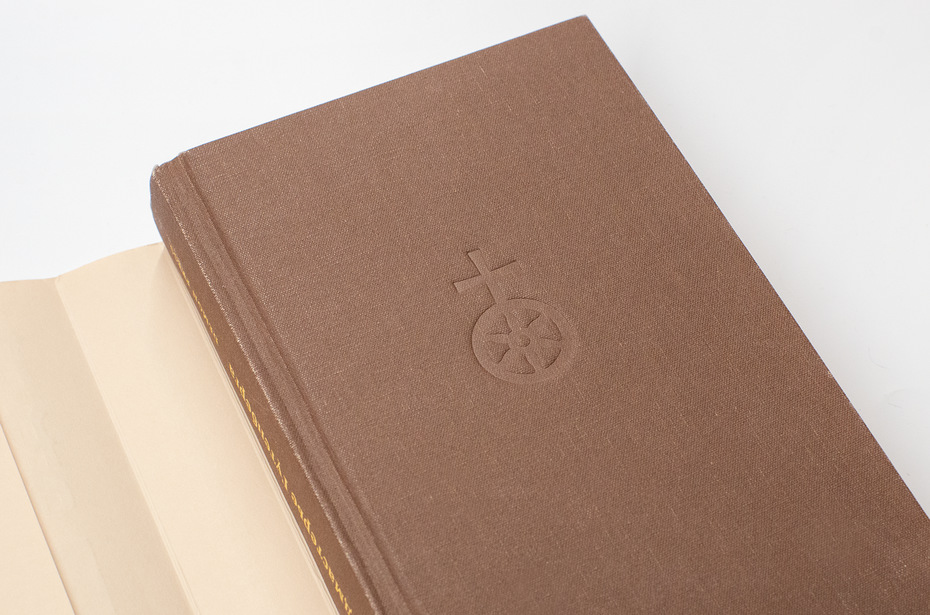
Интервью с «Демонами печати»
На рус­ском язы­ке вы­шел в свет ро­ман «Под­ма­сте­рье Гу­тен­бер­га» аме­ри­кан­ской пи­са­тель­ни­цы Аликс Кри­сти. Ро­ман об од­ном из важ­ней­ших стар­та­пов в ис­то­рии че­ло­ве­че­ства — пе­ча­ти Биб­лии Гу­тен­бер­га. Не­ожи­дан­но, но «Под­ма­сте­рье» по­яви­лся не в од­ном из круп­ных из­да­тельств ху­до­же­ствен­ной ли­те­ра­ту­ры, а в дру­же­ствен­ной нам ма­стер­ской «Де­мо­ны пе­ча­ти». Её ру­ко­во­ди­тель Сер­гей Бе­сов рас­ска­зал, что это впол­не за­ко­но­мер­ный шаг для ма­стер­ской. Мы рас­спро­си­ли его о де­та­лях, по­го­во­ри­ли о бу­ду­щем «Де­мо­нов» как из­да­тель­ско­го про­ек­та и за­од­но по­ин­те­ре­со­ва­лись у шриф­то­во­го ди­зай­не­ра Оле­га Ма­цу­е­ва о шриф­те для но­вой кни­ги.
По­че­му вы ре­ши­ли из­дать кни­гу, причём ху­до­же­ствен­ную и пе­ре­вод­ную?
Кни­гу «Под­ма­сте­рье Гу­тен­бер­га» на ан­глий­ском нам по­да­рил Иван Гуль­ков, и по­на­ча­лу мне бы­ло тя­же­ло её чи­тать, хо­тя я во­об­ра­жал, что кни­га под­толк­нёт ме­ня к изу­че­нию язы­ка, и да­же во­зил с со­бой сло­варь и тет­рад­ку. Чи­та­тель­ский се­зон у ме­ня на­чи­на­ет­ся осе­нью — я ино­гда ез­жу на мет­ро  и там по­чи­ты­ваю кни­ги.
Я при­ез­жал на ра­бо­ту и пе­ре­ска­зы­вал всем оче­ред­ную гла­ву, как се­ри­ал. Рас­ска­зы­вал и про Пе­те­ра Шёф­фе­ра, и про то, как они по­тра­ти­ли огром­ные день­ги на за­пуск пе­чат­но­го стан­ка. Как-то я пришёл и го­во­рю: «Слу­шай­те, они там ре­ша­ют важ­ную про­бле­му, в один цвет пе­ча­тать кни­гу или в два!» Или: «Гу­тен­бер­га-то за­бра­ли!» На сле­ду­ю­щий день: «Гу­тен­бер­гу всё на­до­е­ло!» Если серьёз­но, то кни­га Аликс Кри­сти ин­те­рес­на с ис­то­ри­че­ской точ­ки зре­ния, не толь­ко сю­жет­ной. Да­же то, как бы­ла устро­е­на ма­стер­ская Гу­тен­бер­га, глу­бо­ко вол­но­ва­ло, по­то­му что мно­гое из кни­ги на­по­мни­ло мне о на­шей ма­стер­ской.
Мы дав­но меч­та­ли из­дать что-то об ис­то­рии пе­ча­ти и тех­но­ло­гий пе­ча­ти. И тут яви­лась эта кни­га. Же­ня  од­на­жды пришёл и ска­зал: «Да­вай­те её из­да­дим по-рус­ски». Окей, ре­ши­ли, а что для это­го нуж­но сде­лать? Все­го-то ку­пить пра­ва, пе­ре­ве­сти — всё в на­ших си­лах.
Мож­но по­дроб­нее о по­куп­ке прав на кни­гу?
Хва­ла ин­тер­не­ту — я про­сто ра­зыскал в фейс­бу­ке ав­то­ра, Аликс Кри­сти, и на­пи­сал ей в том же ду­хе: мол, чи­тал кни­гу в мет­ро, очень по­нра­ви­лось, хо­ро­шо бы её из­дать на рус­ском. Она очень бы­стро от­ве­ти­ла, ска­за­ла, что ра­бо­та­ет с агент­ством William Morris. Обыч­но, до­ба­ви­ла она, мы не ра­бо­та­ем с ма­стер­ски­ми или част­ны­ми ли­ца­ми, но если вы so enthusiastic, то по­че­му бы и нет? Как ока­за­лось, у них есть пред­ста­ви­тель­ство в Моск­ве, в ко­то­ром ме­ня по­зна­ко­ми­ли с Люд­ми­лой Суш­ко­вой. Мне уда­лось её убе­дить, что де­ло сто­я­щее, и пе­ре­го­во­ры ве­ла уже она от на­ше­го име­ни. Это бы­ло в на­ча­ле 2017 го­да.
Как ис­ка­ли пе­ре­вод­чи­ка и по­че­му оста­но­ви­лись на Мак­си­ме Нем­цо­ве?
На­чи­на­лось всё пре­крас­но: кни­га есть на ру­ках, Аликс (ав­тор кни­ги) да­ла до­бро, агент­ство в по­ряд­ке, пе­ре­вод­чик то­же нашёл­ся за­ме­ча­тель­ный. Мы пла­ни­ро­ва­ли вы­пу­стить рус­ский пе­ре­вод че­рез пол­го­да. Сна­ча­ла до­го­во­ри­лись с Сер­ге­ем Ильи­ным . Мы по­смот­ре­ли, кто что пе­ре­во­дит, поспра­ши­ва­ли зна­ко­мых — очень хо­те­ли най­ти пе­ре­вод­чи­ка вы­со­ко­го полёта, при­том что в этой об­ла­сти мы нео­фи­ты — сла­бо раз­би­ра­ем­ся как в ан­гло­языч­ной ли­те­ра­ту­ре, так и в кни­го­из­да­тель­стве в це­лом. Я успел съез­дить к Сер­гею Ильи­ну, по­зна­ко­мил­ся с ним. Он про­из­вёл на ме­ня силь­ное впе­чат­ле­ние, и мы обо всём до­го­во­ри­лись. Но про­изо­шло не­сча­стье: Ильин умер. Это ме­ня до­воль­но силь­но под­ко­си­ло. Я ред­ко ез­жу на по­хо­ро­ны, но на по­хо­ро­нах Ильи­на я по­бы­вал.
Даль­ше на­ча­лись слож­но­сти. Мы вновь обра­ти­лись к зна­ко­мым пи­шу­щим лю­дям, и в ка­кой-то мо­мент воз­ник­ло имя Мак­си­ма Нем­цо­ва. Агент­ство то­же ска­за­ло: «Кру­то, ко­неч­но, да­вай­те с ним!» По­том я вы­яс­нил, что од­на из мо­их лю­би­мых книг «Дз­эн и ис­кус­ство ухо­да за мо­то­цик­лом» пе­ре­ве­де­на Нем­цо­вым. Мне по­ка­за­лось, что пазл сло­жил­ся. Я на­пи­сал ему пись­мо и при­ло­жил PDF с кни­гой. Макс от­ве­тил, что возь­мёт­ся за эту ра­бо­ту. Я, ра­зу­ме­ет­ся, не имел пред­став­ле­ния о том, как он пе­ре­во­дит и ка­кие имен­но кни­ги, но счи­таю это зна­ком­ство ча­стью из­да­тель­ско­го опы­та. Ре­дак­тор на­шей кни­ги Ша­ши Мар­ты­но­ва то­же с ним мно­го ра­бо­та­ла.
Что ты ду­ма­ешь о Гу­тен­бер­ге в ро­ма­не? У Аликс Кри­сти он вы­ве­ден ти­ра­ном, эта­ким Фа­у­стом, ко­то­рый по­до­зре­ва­ет весь мир в кра­же идей, по­сто­ян­но бо­ит­ся че­го-то. И ему про­ти­во­по­став­лен Пе­тер Шёф­фер, неж­ный и меч­та­тель­ный тру­дя­га.
Ме­ня та­кое про­чте­ние лич­но­сти Гу­тен­бер­га очень за­ин­те­ре­со­ва­ло. Ко­гда-то я по­мо­гал доч­ке в четвёр­том клас­се де­лать до­клад про не­го. Ну что я знал о Гу­тен­бер­ге? За­хо­дишь в Ви­ки, чи­та­ешь все эти скуч­ные справ­ки. Они до­воль­но су­хие, и, если ты не до­бав­ля­ешь ка­ких-то по­дроб­но­стей и об­ра­зов, ты не мо­жешь се­бе пред­ста­вить мас­шта­ба изоб­ре­те­ния Гу­тен­бер­га. Аликс Кри­сти, ко­неч­но, ре­кон­стру­и­ру­ет со­бы­тия, мно­гое при­ду­мы­ва­ет, но есть об­сто­я­тель­ства, в ко­то­рые я лич­но ве­рю. Они вдруг на­чи­на­ют ре­зо­ни­ро­вать с ве­ща­ми, ко­то­рые про­ис­хо­дят с на­ми сей­час. Мо­жет быть, ко­неч­но, она и са­ма ис­хо­ди­ла из зна­ний о со­вре­мен­ном ми­ре — о стар­та­пах, но­вых тех­но­ло­ги­ях и про­чем. С дру­гой сто­ро­ны, есть не­кие уни­вер­саль­ные те­мы, ко­то­рые спу­стя 600 лет не силь­но из­ме­ни­лись. К та­ким ве­щам от­но­сит­ся и че­ло­ве­че­ская при­ро­да.
Я рас­ска­зы­вал, что ко­гда мы с Же­ней толь­ко на­чи­на­ли наш про­ект «Де­мо­ны пе­ча­ти», то я сра­зу по­чув­ство­вал, что его де­я­тель­ность в ма­стер­ской «Кли­ше» — это хо­ро­шо и ка­че­ствен­но сде­лан­ная ра­бо­та. Мне не нуж­но дол­го объ­яс­нять до­сто­ин­ства хо­ро­шей ра­бо­ты, я чув­ствую это сра­зу. Вот ров­но та­кое же впе­чат­ле­ние ме­ня не по­ки­да­ло, ко­гда я чи­тал кни­гу Аликс Кри­сти. И не важ­но, на­сколь­ко прав­ди­ва её ре­кон­струк­ция чувств и мыс­лей Гу­тен­бер­га, по­то­му что про­бле­мы, с ко­то­ры­ми стал­ки­ва­ют­ся ге­рои кни­ги в про­цес­се со­зда­ния Биб­лии, и се­го­дня ак­ту­аль­ны.
То есть во мно­гом это кни­га о про­из­вод­ствен­ной стра­сти, ко­то­рая пол­но­стью по­гло­ща­ет че­ло­ве­ка.
Это пер­вое, да. А вто­рое, что мы сра­зу вы­хва­ты­ва­ем из ро­ма­на Кри­сти,— это то, на­сколь­ко ва­жен ди­зайн, идея. Гу­тен­берг ведь и до Шёф­фе­ра  умел пе­ча­тать. Но это был со­вер­шен­но дру­гой уро­вень. И мне ка­жет­ся, что эта кни­га цен­на как пу­те­во­ди­тель для ди­зай­не­ра или для лю­бо­го де­ла­ю­ще­го что-то че­ло­ве­ка. Ди­зайн не то что­бы спасёт мир, но он при­вно­сит в мир очень мно­гое.
Шриф­то­ли­тей­ная фор­ма — устрой­ство, в ко­то­рое по­ме­ща­лась мат­ри­ца с вы­би­тым на ней изоб­ра­же­ни­ем бук­вы (знак вы­би­ва­ли пу­ан­со­ном). Сло­во­лит­чик на­пол­нял по­лость фор­мы спе­ци­аль­ным сп­ла­вом, и по­сле за­твер­де­ва­ния фор­му мож­но бы­ло ра­зо­мкнуть — так по­лу­ча­лась ли­те­ра с ре­льеф­ным изоб­ра­же­ни­ем зна­ка.
В ито­го­вой вер­сии вёрст­ки ко­лон­ти­ту­лы ре­ши­ли уб­рать.